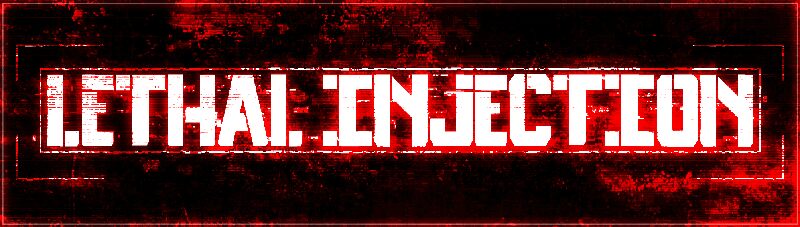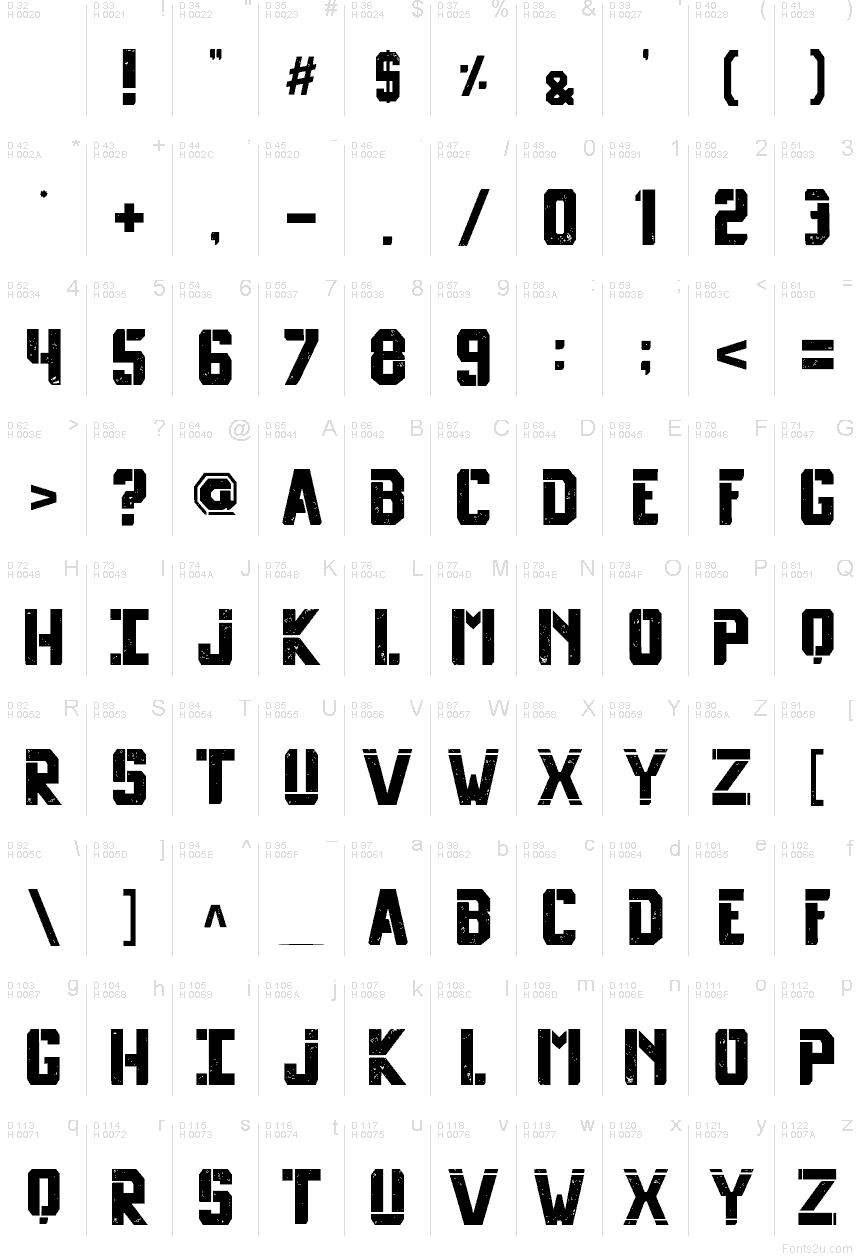
Lethal Injection Scuffe Regular
Lethal Injection Scuffe to darmowy, wojskowy krój pisma typu display o erodowanej fakturze, wyróżniający się tępymi, blokowymi wielkimi literami i powierzchnią przypominającą odpryskującą farbę. Litery zaprojektowano z myślą o wyrazistości: wysokie, ciężkie kształty, kwadratowe krawędzie i przetarte odstępy nadają alfabetowi charakter wojskowego szablonu, nie popadając przy tym w przesadnie industrialny styl.
Świetnie sprawdzi się na plakatach, okładkach albumów, w tytułach gier, ulotkach eventowych oraz w grafikach na odzieży, gdzie darmowy font z "pazurem" wygląda bardziej przekonująco niż czysta, elegancka czcionka. Używaj go w krótkich nagłówkach, monogramach lub wyrazistych hasłach, gdy chcesz, by wielkie litery wyglądały jak zwietrzałe oznaczenia wybite na metalu, skrzyniach lub starym ekwipunku polowym.
Lethal Injection Scuffe Regular — Prezentacja czcionki
Lethal Injection Scuffed